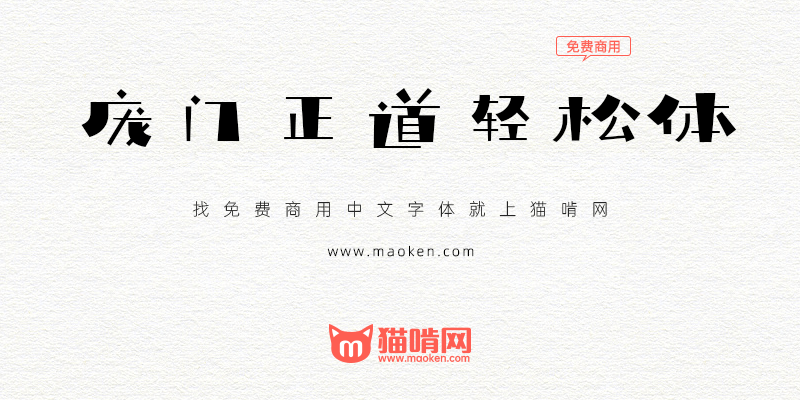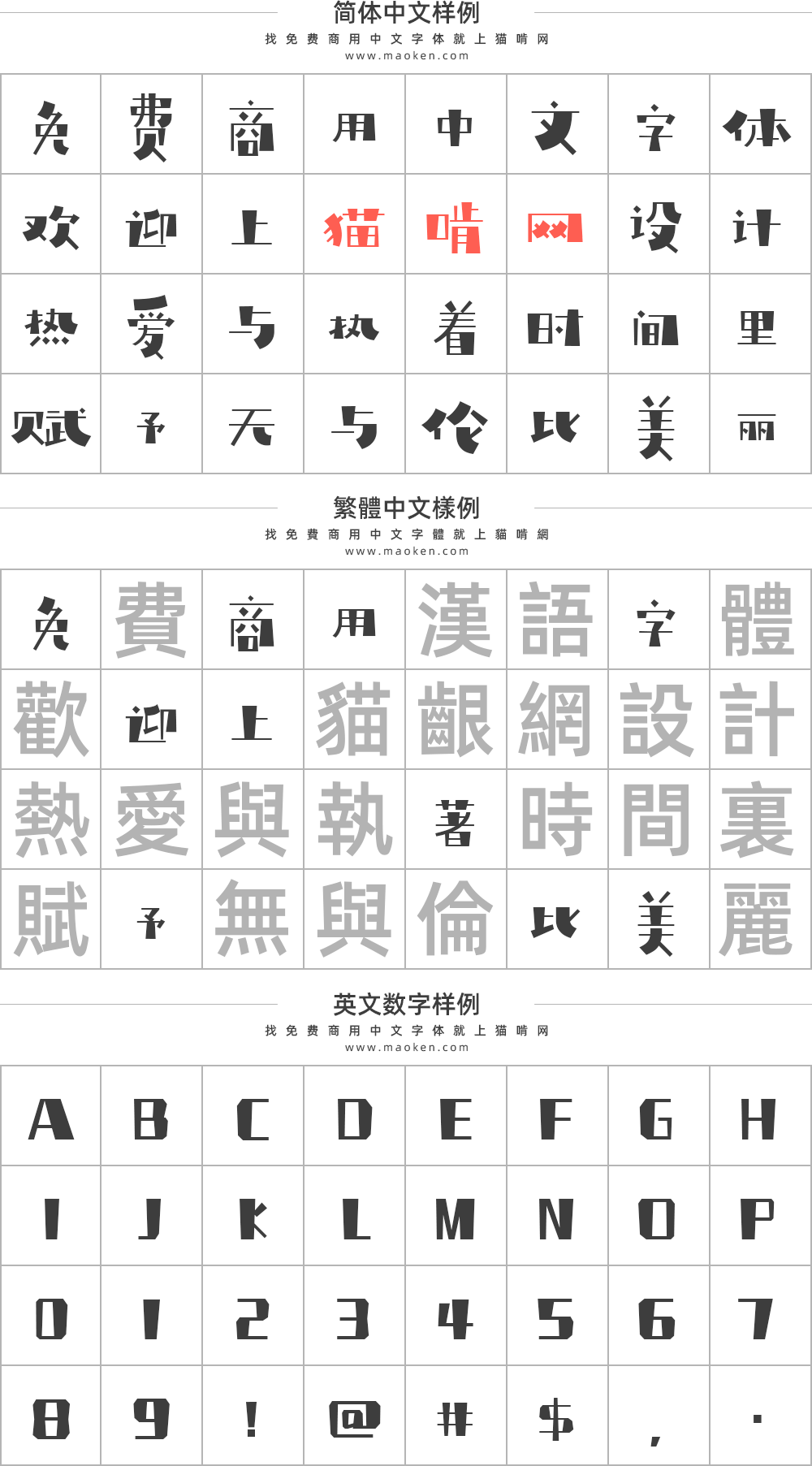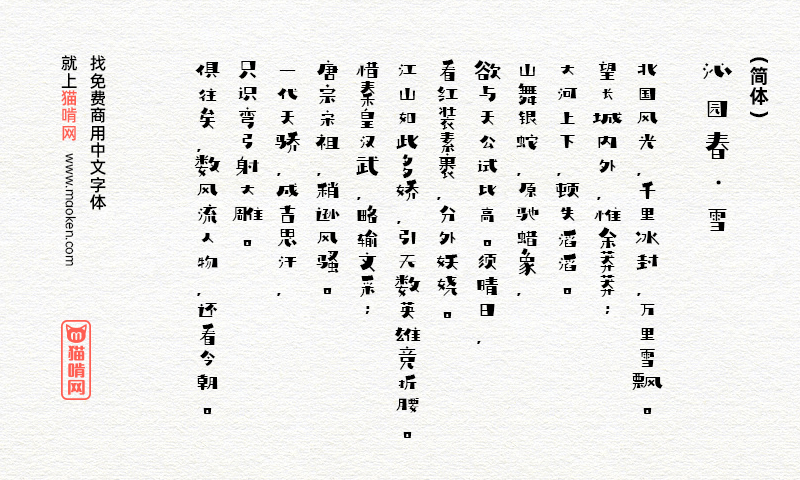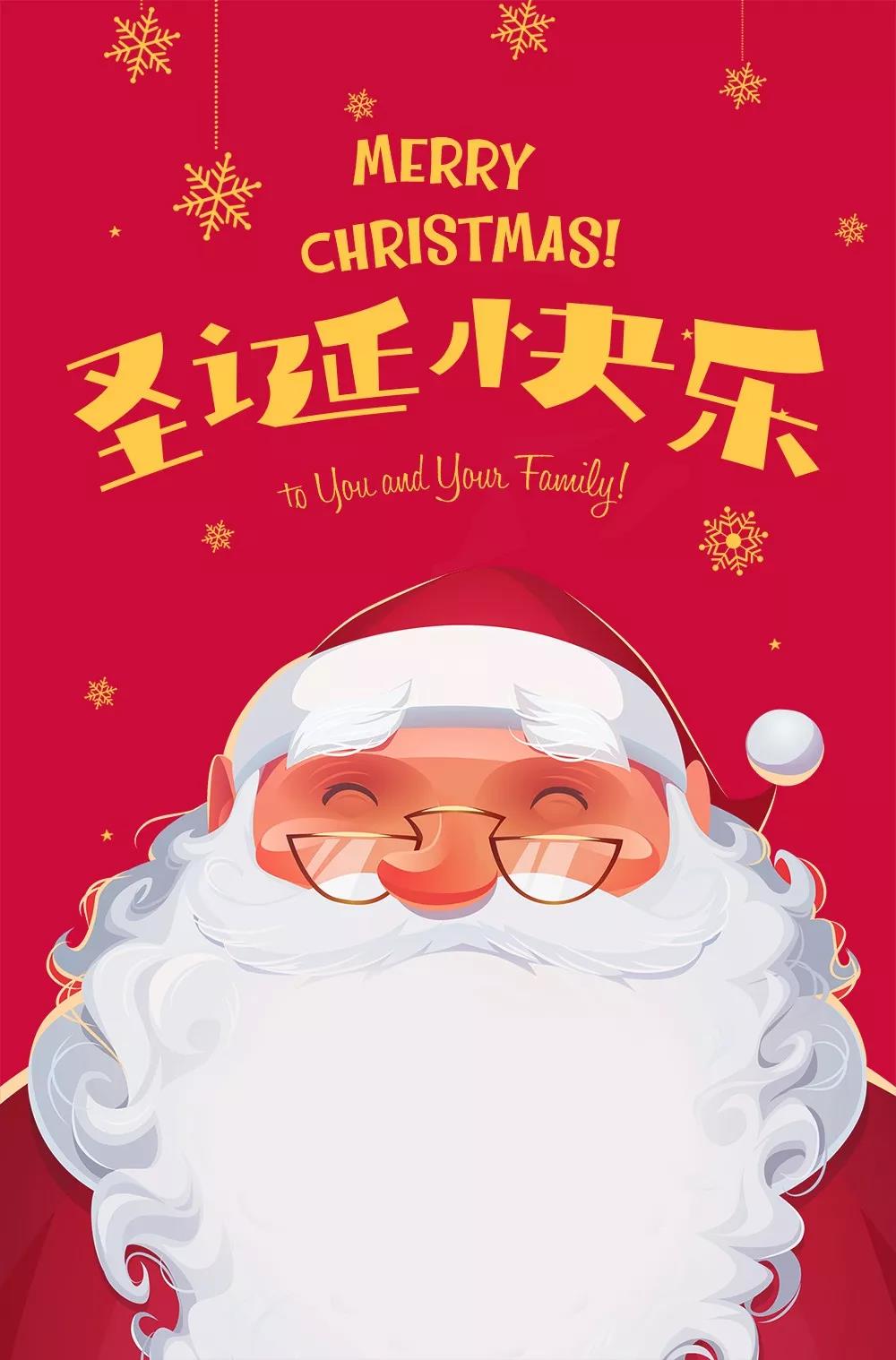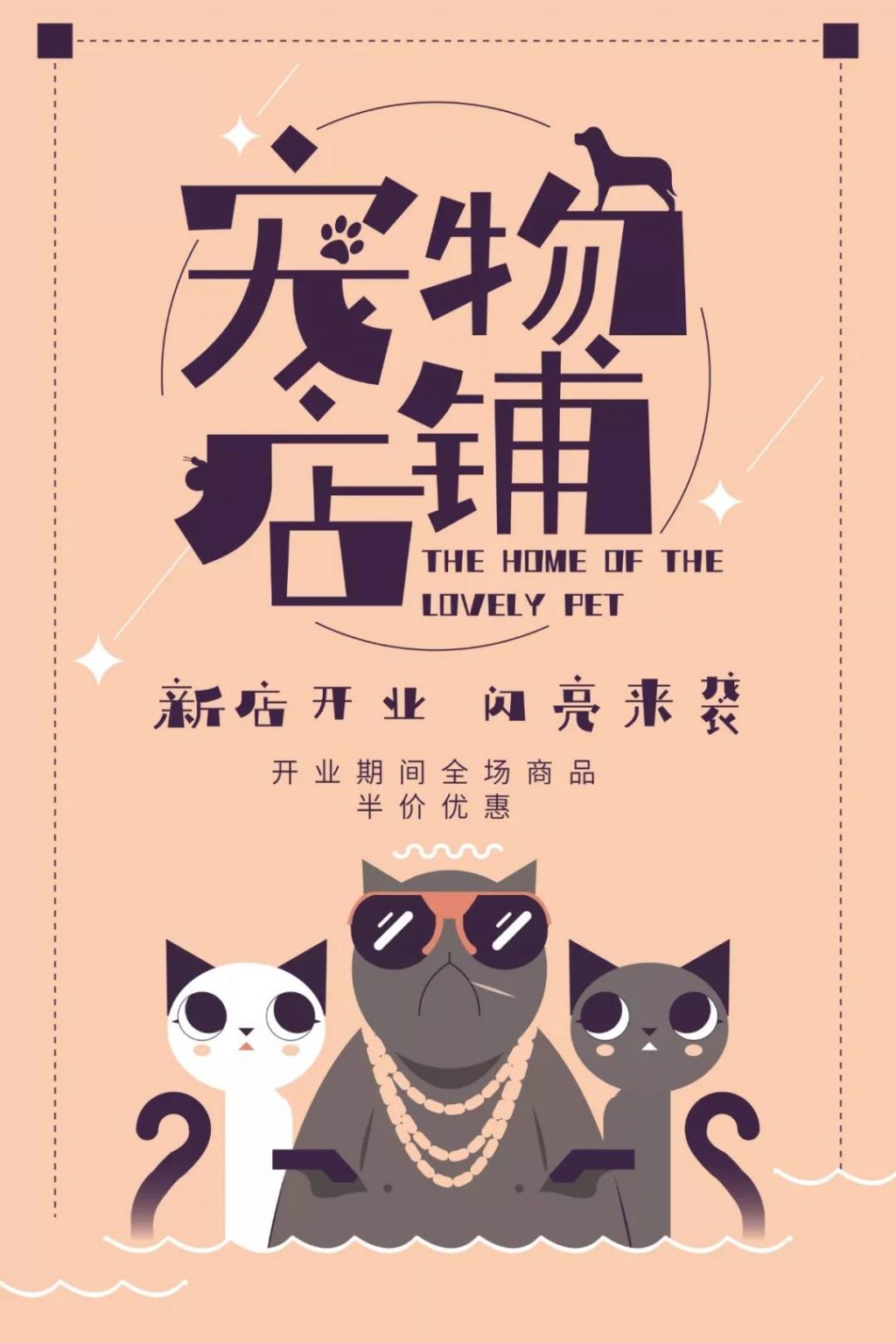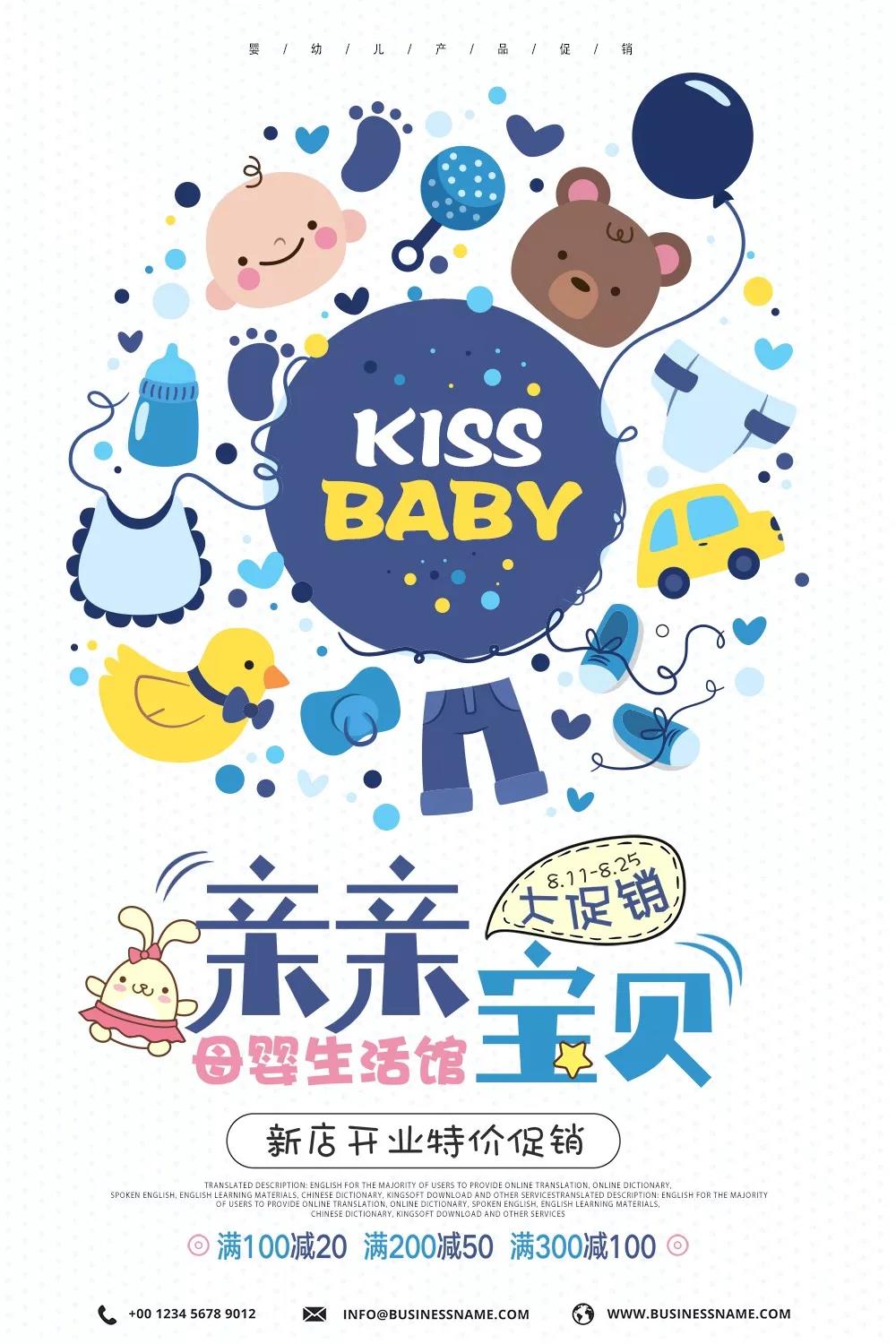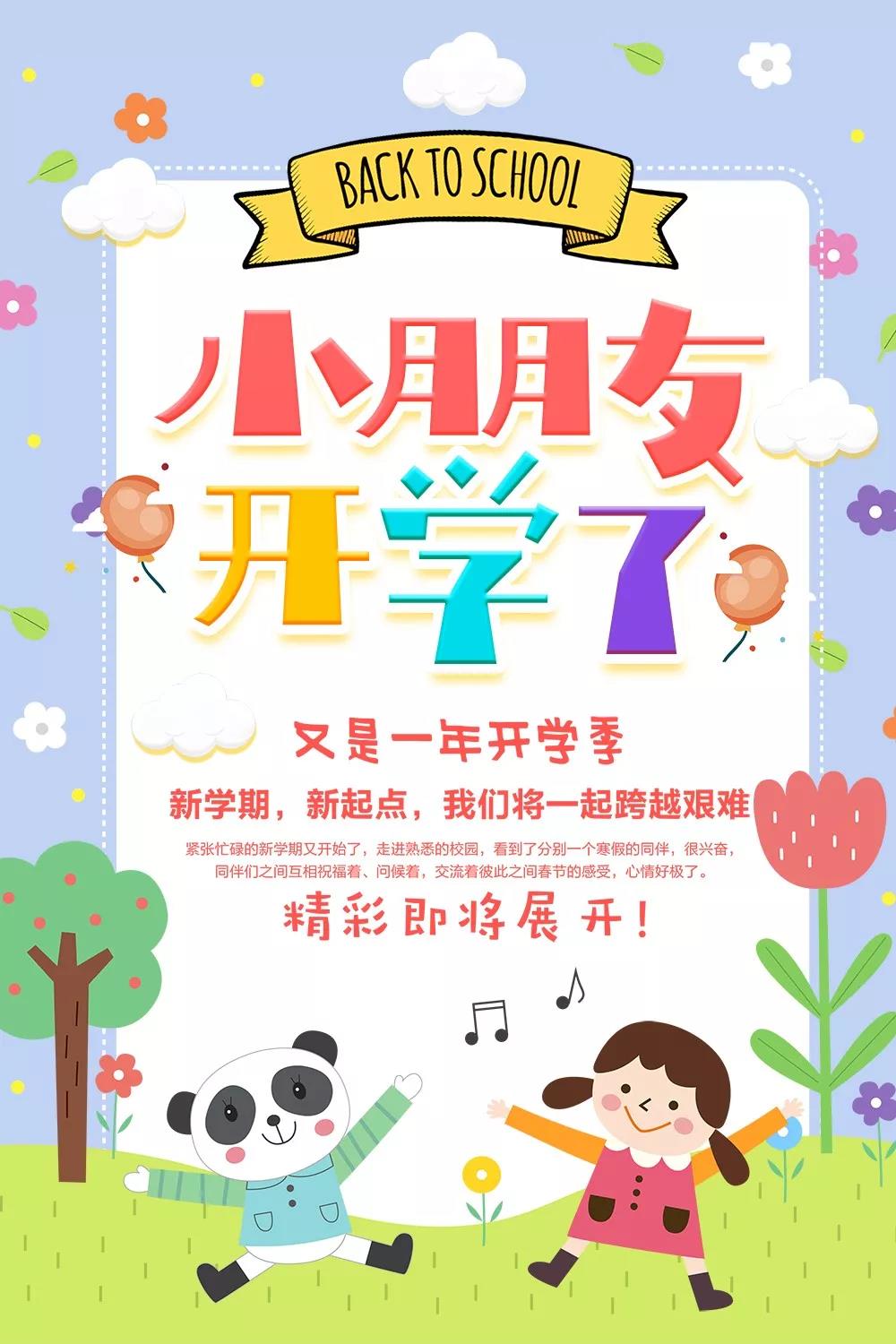
庞门正道轻松体:庞门正道第三套免费商用字体重磅上线
字体作者:刘兵克工作室 (中国大陆) 字体字重:1个
字体作者:庞门正道 x 刘兵克(中国大陆) 字体字重:1个
2019年12月5日,在这个特别的日子里,庞门正道第三套免费商用字体庞门正道轻松体正式上线。这款字体是刘兵克字体设计班的学生在自愿的原则下,一共78位学员经过了一年的努力开发的字体。这是一次免费的公益字库的设计,大家都是没有额外的金钱报酬的,仅仅是为了社会公益,社会价值。
庞门正道轻松体字库风格非常可爱蠢萌,带着些许的俏皮的,趣味十足,字形活泼非常适合宠物,儿童等方面的设计。